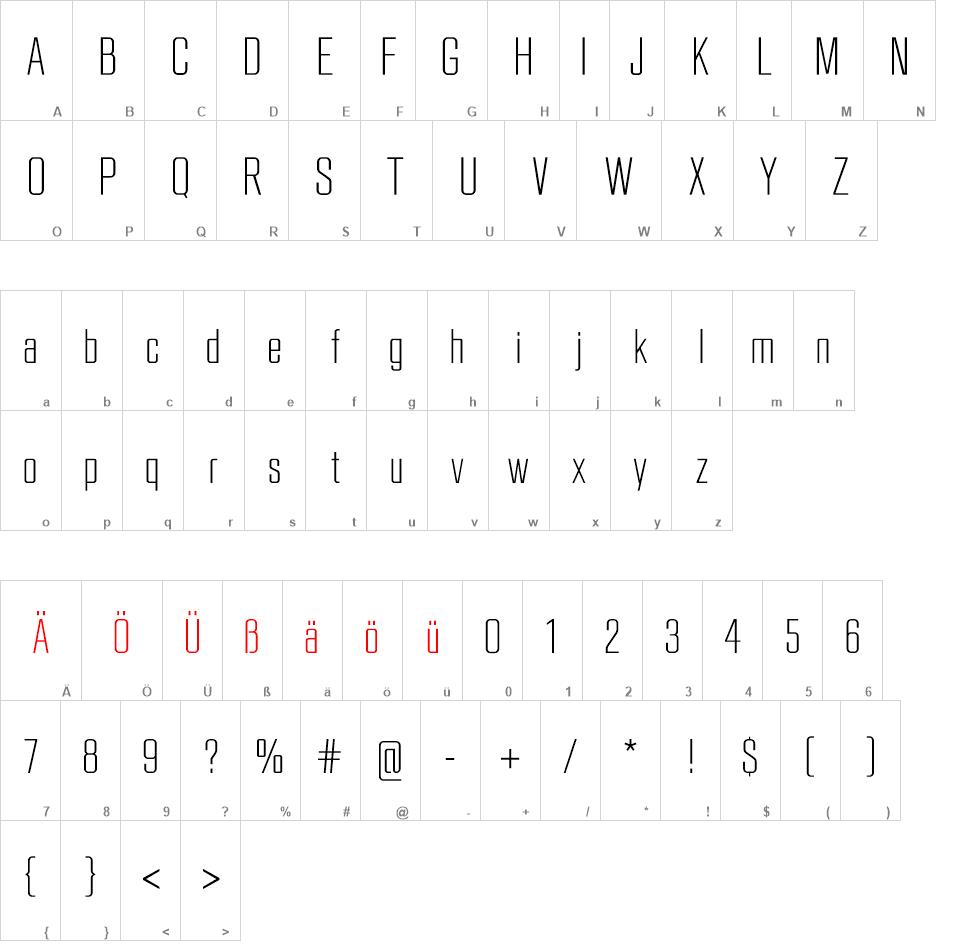
RBNo2
RBNo2  font
Es wurde von industriellen Schriften aus dem späten 19. Jahrhundert deutscher Herkunft inspiriert, über Gleichmäßigkeit und Geometrie. In Kombination mit anderen Sans-Serifen, Billet-Serifen und Serif-Fonts fällt dies in den Überschriften und Texten des Kurztextes auf. Zusätzlich zu normalen Stilen werden alternative Versionen die Schrift zu einem perfekten Partner für zeitgenössische, technische und zeitgenössische Eindrücke sowie für hochwertige, luxuriöse und zeitlose Umgebungen machen.